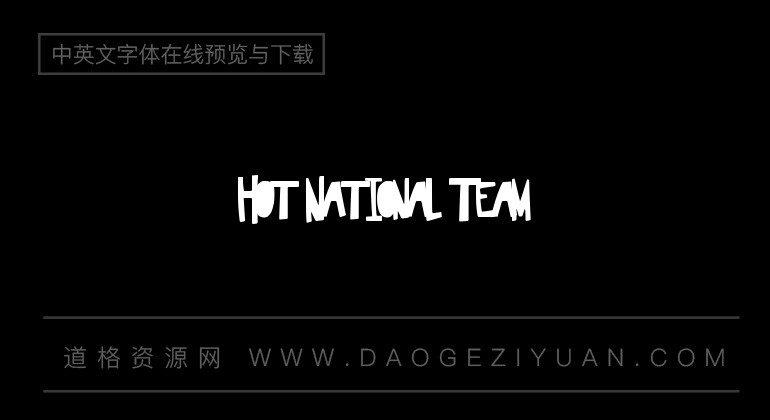
Hot National Team
? Hot National Team 字体是一种特殊的字体,它的特点在于它的字母设计简单,比较粗犷,而且有一种激情的气息,让人联想到体育队伍的风格。它的字母采用粗体,而且有一些特殊的设计,比如曲线和尖角,使得它看起来更有力量和活力。它还有一些特殊的字母,比如“V”、“X”和“Z”,使得它更有视觉冲击力。
Hot National Team是一款非常不错的手写艺术字体,具有很好的视觉感,适合于文化类的宣传设计、商业类品牌的广告和产品包装设计以及个性化文字排版等较多场景。